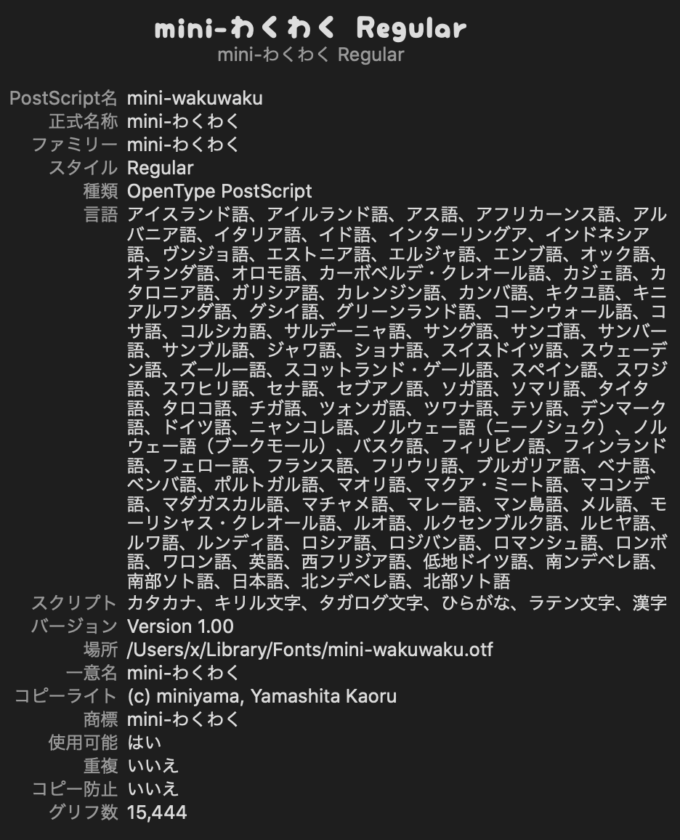
mini-わくわく
りんごひめ
The Creative Fonts Bundle: 5 Fonts For Free
5種類のかわいらしいフォントを無料でダウンロードすることができます。
ぱぐみんちょ
プぷプ
ドラネコ ボールド
ぽめらにあんフォント
はんでぃーはーとねお
ボコスカモンスター
ステッチフォント
Nu らっかせい
にくまるフォント
ふわもこフォント
ドーナツショップ
まろみん
しあさって
ポプらむ☆キュート
FANCY NANCY
ぱんきじ
ぼてりん